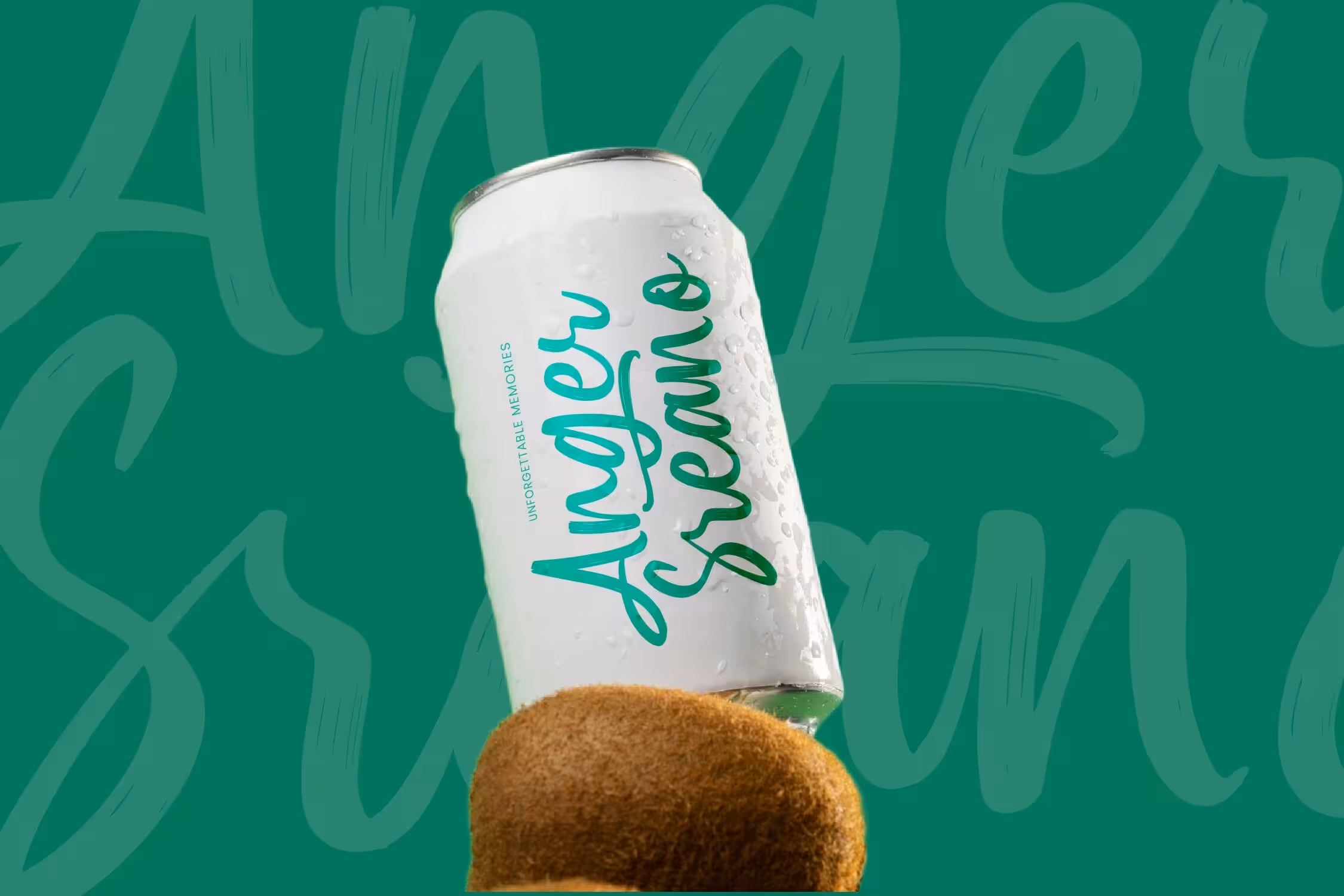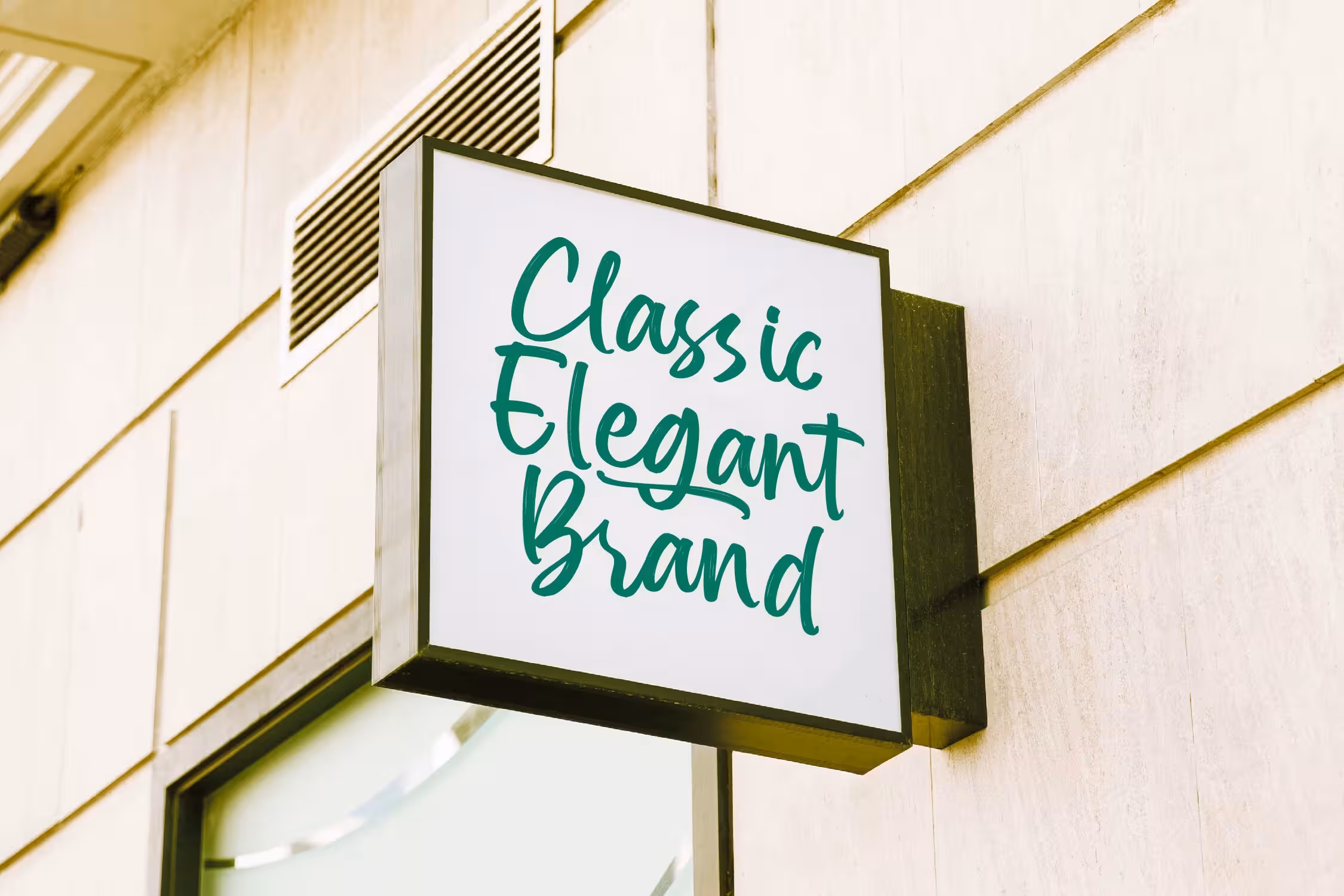
Giới thiệu về Font TF Broften Storetta Việt hóa
TF Broften Storetta Việt hóa là một font chữ kiểu cọ (brush font) nổi bật với thiết kế nét cọ tự do, phóng khoáng và đầy cá tính. Font này mang đến vẻ ngoài nghệ thuật, năng động và một chút bụi bặm, gợi cảm giác về những nét vẽ tay được thực hiện bằng cọ một cách chân thực và có hồn. Đây là lựa chọn lý tưởng để tạo điểm nhấn độc đáo và thu hút mọi ánh nhìn trong các thiết kế đòi hỏi sự sáng tạo và phong cách riêng.
Với đặc điểm là nét brush tự nhiên, phong thái mạnh mẽ và tính ứng dụng cao, Broften Storetta là lựa chọn lý tưởng cho các thiết kế muốn truyền tải sự độc đáo, cá tính và sự gần gũi của nghệ thuật thủ công:
- Thiết kế túi vải: Hoàn hảo để in các tên thương hiệu, slogan, họa tiết chữ hoặc hình ảnh minh họa lên túi vải canvas, túi tote. Nét cọ mạnh mẽ và tự do của font sẽ làm cho chiếc túi trở nên cá tính, phong cách và thu hút sự chú ý. Đây là lựa chọn tuyệt vời cho các thương hiệu thời trang hướng đến phong cách độc đáo, handmade hoặc nghệ thuật.
- In ấn: Lý tưởng cho các ấn phẩm in ấn cần sự tác động thị giác mạnh mẽ như áp phích (poster), banner quảng cáo, hoặc các ấn phẩm khuyến mãi. Font này đảm bảo khả năng đọc tốt ngay cả ở kích thước lớn, và tạo hiệu ứng nghệ thuật khi in trên mọi chất liệu.
- Thiết kế áo thun: Phù hợp để in các câu trích dẫn, thông điệp cá nhân hoặc họa tiết chữ lên áo phông, áo hoodie. Nét cọ của font sẽ giúp áo thun trở nên nổi bật, phong cách và truyền tải thông điệp một cách cá tính.
- Thiết kế bao bì sản phẩm: Có thể dùng cho các sản phẩm thủ công, đặc sản địa phương, hoặc các mặt hàng muốn truyền tải sự độc đáo và chất lượng của sản xuất thủ công.
Với TF Broften Storetta Việt hóa, bạn có thể dễ dàng thổi hồn nghệ thuật, sự cá tính và vẻ đẹp mộc mạc vào các thiết kế, tạo ra những sản phẩm không chỉ đẹp mắt mà còn đầy cảm xúc và sức hút đặc biệt.